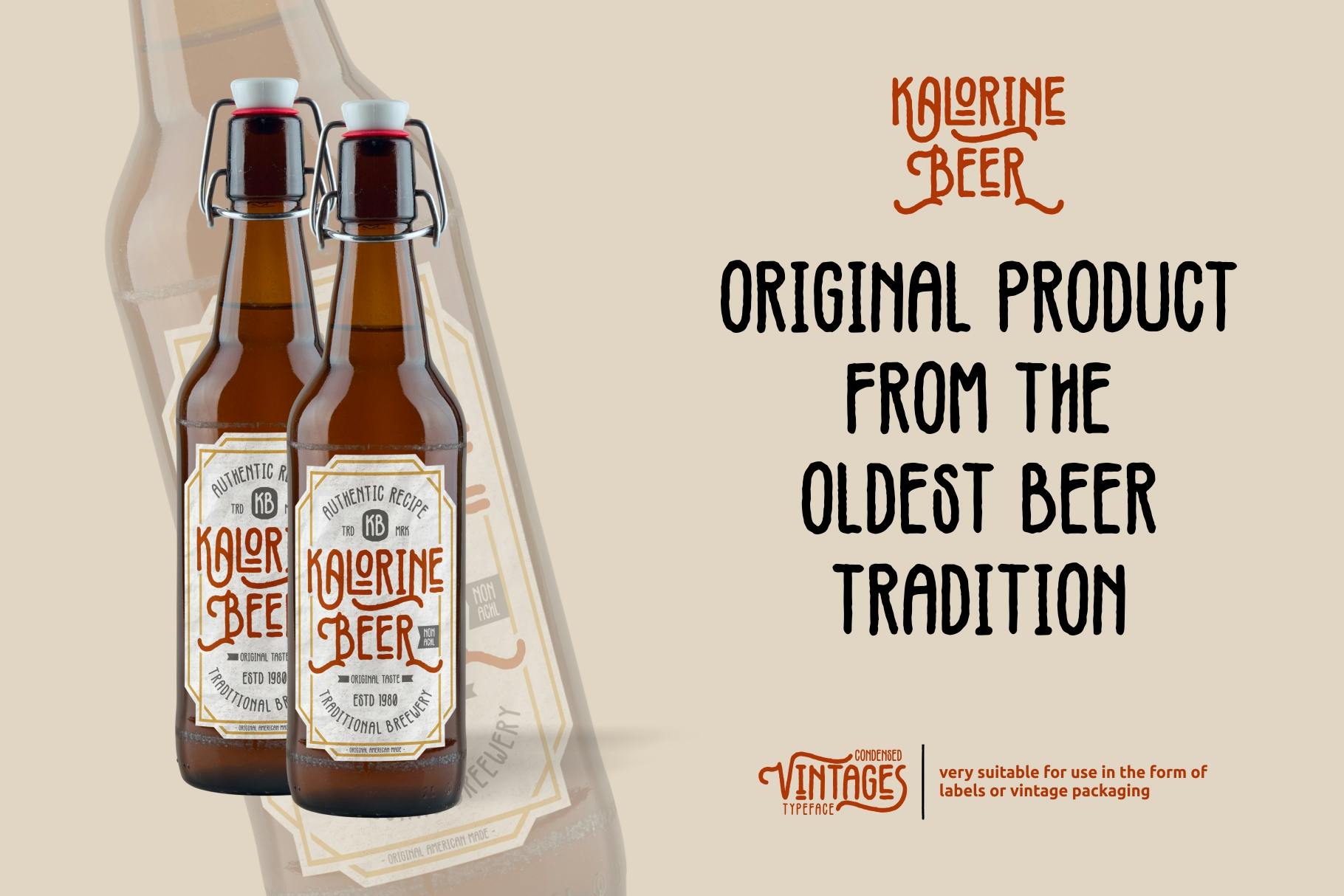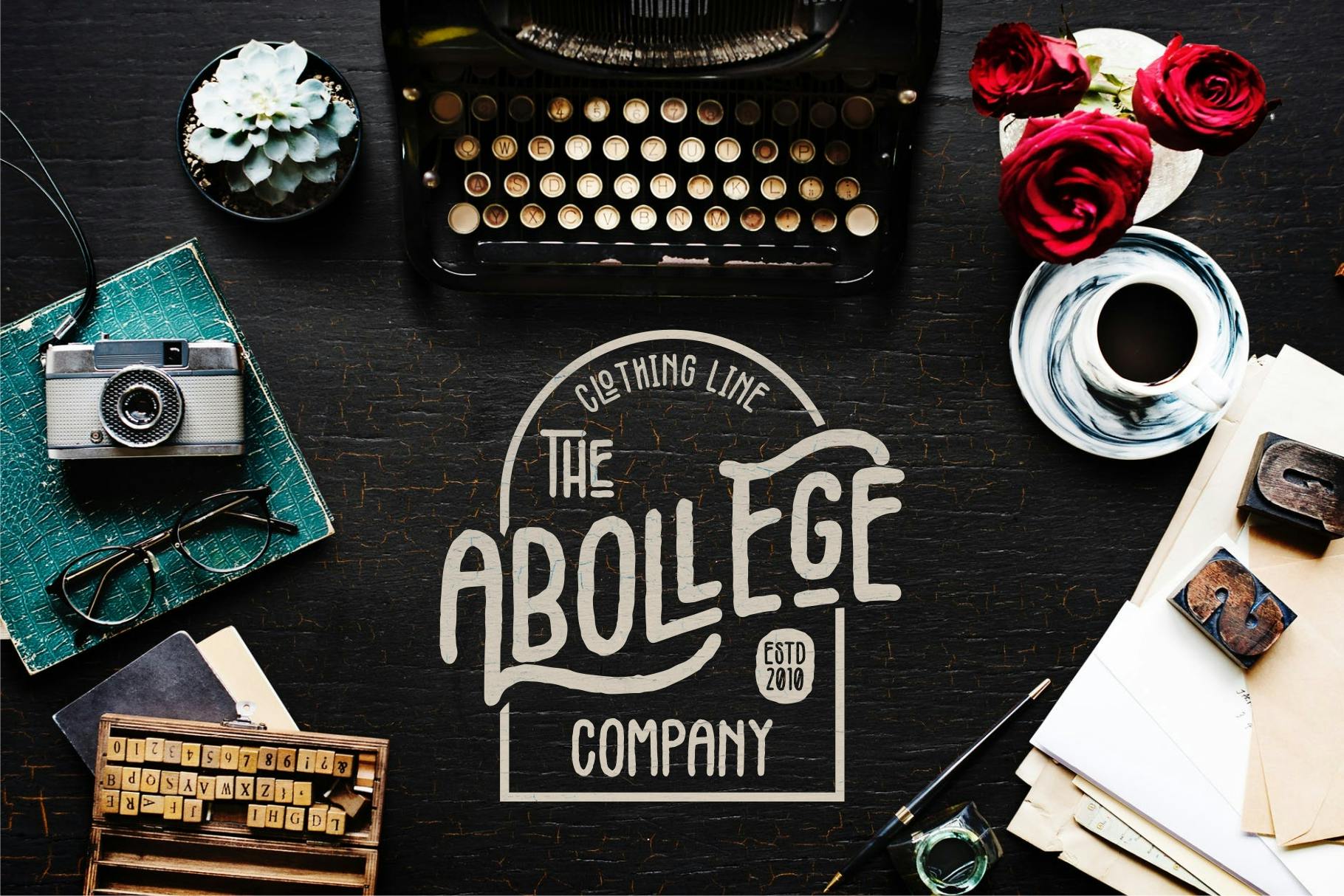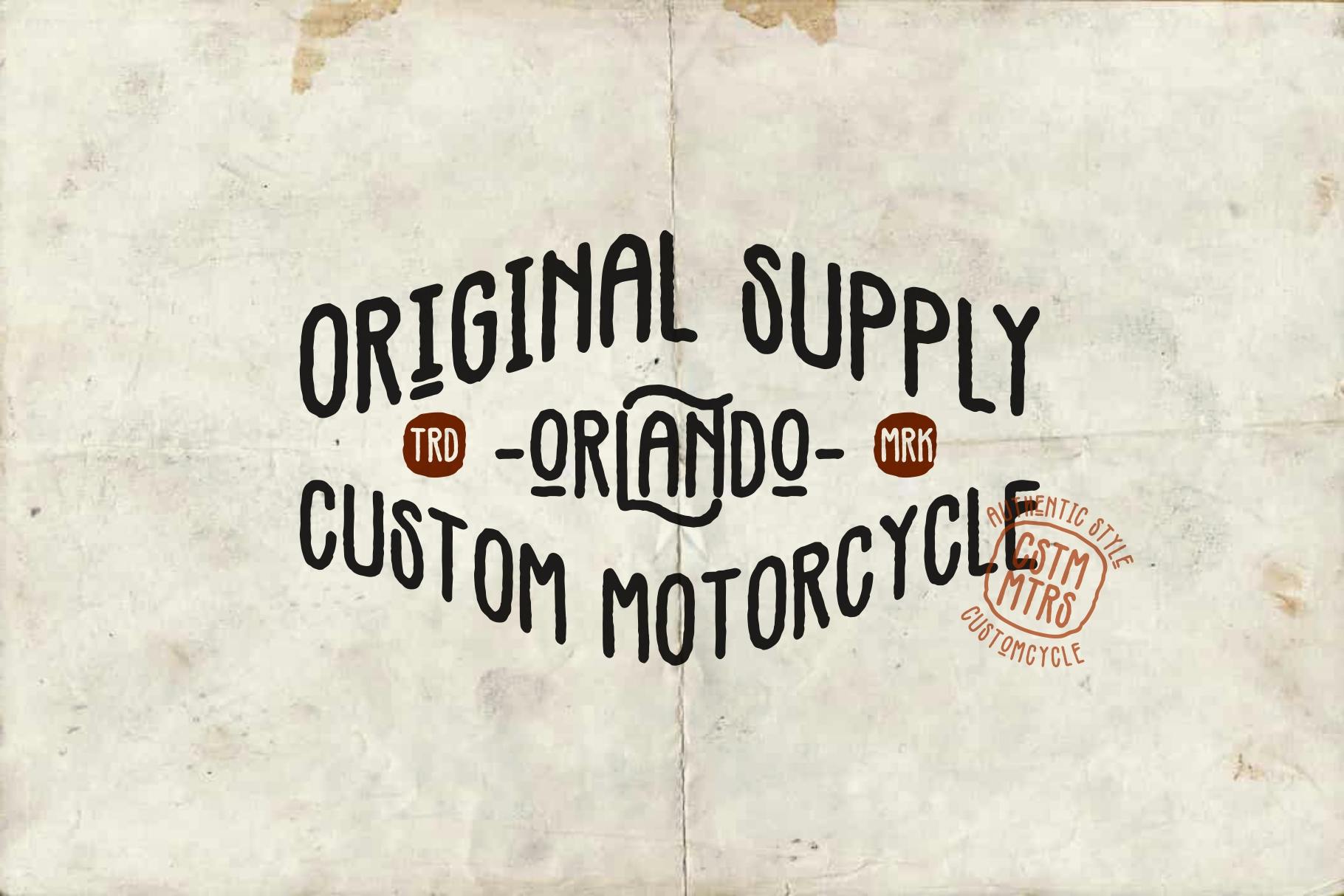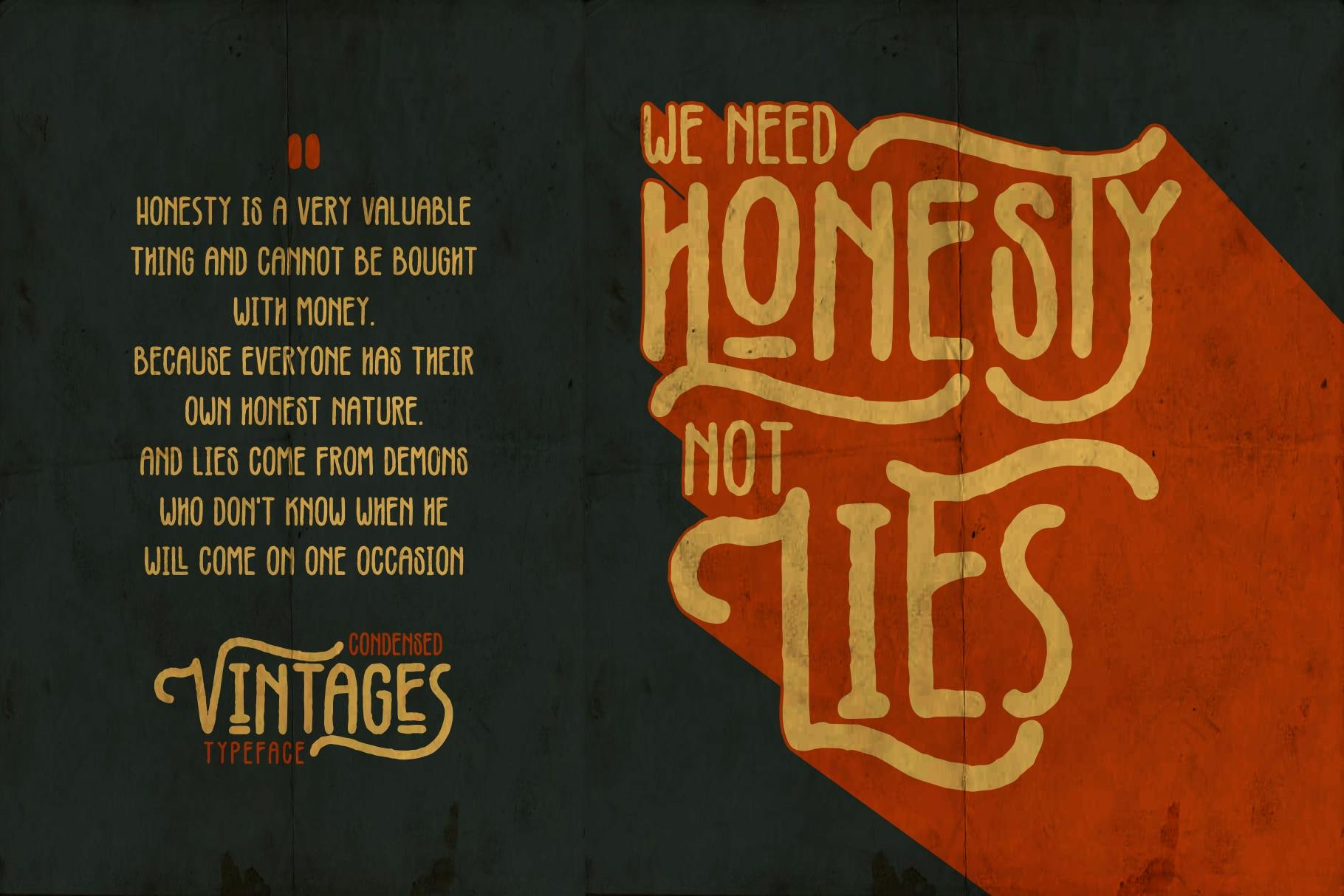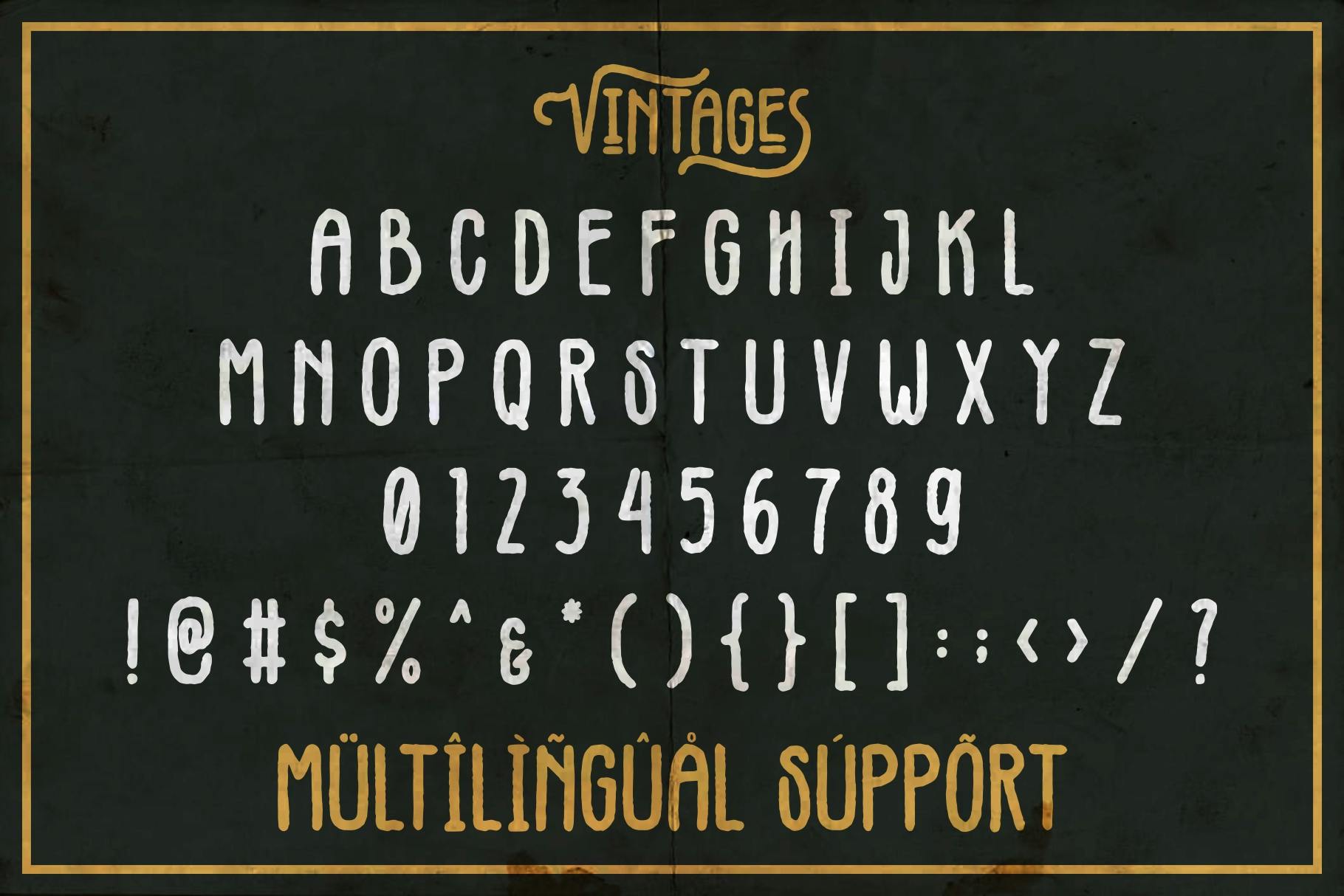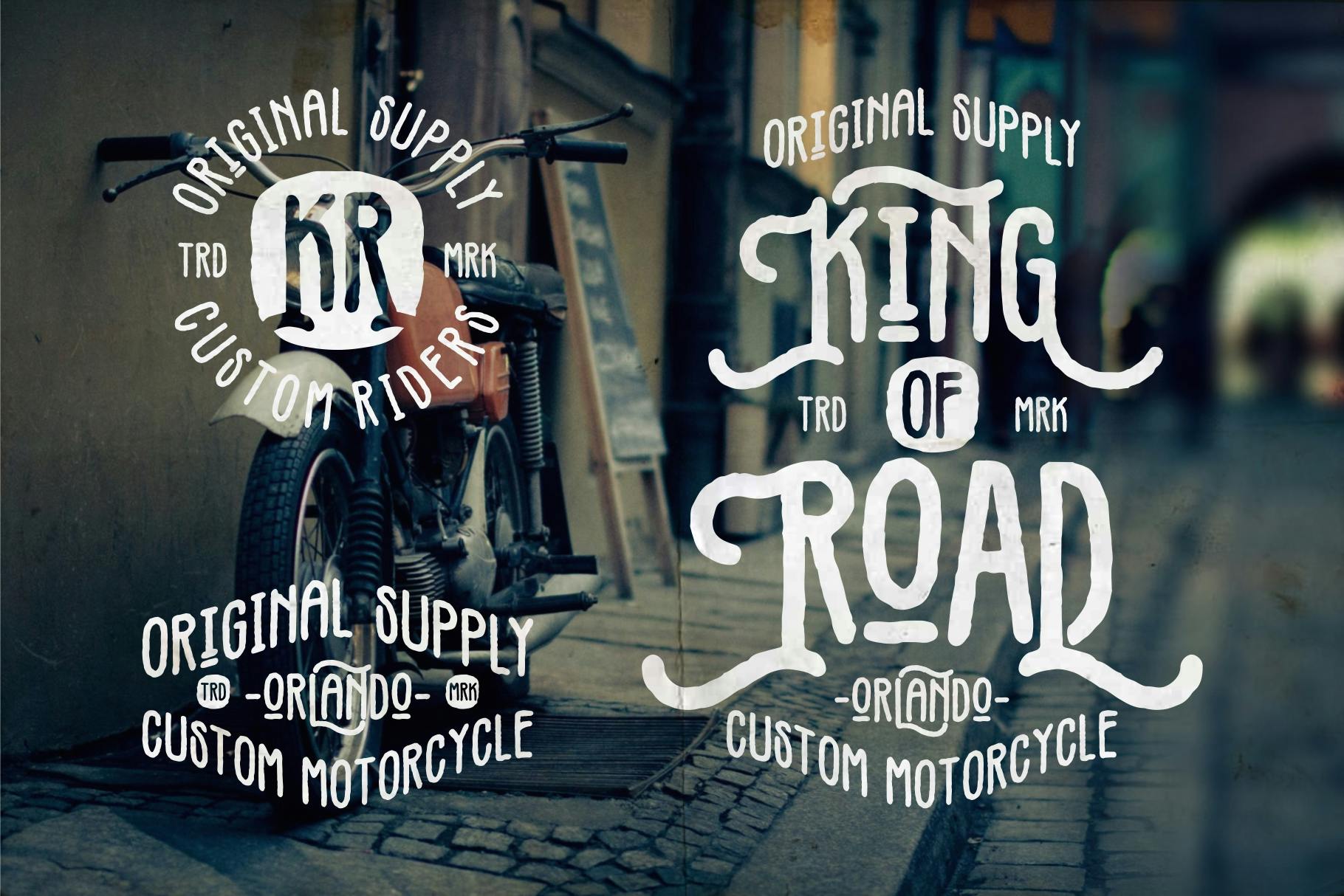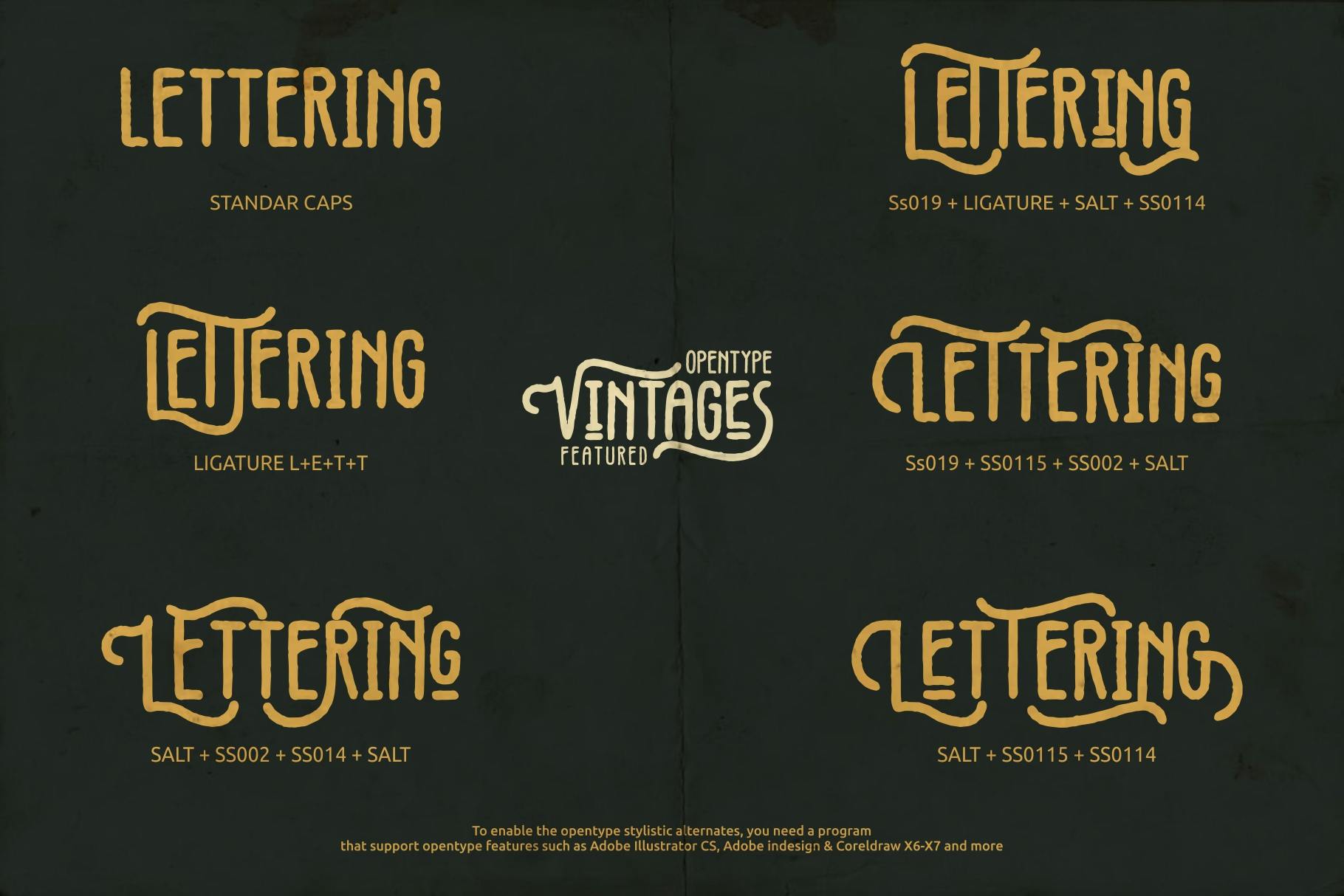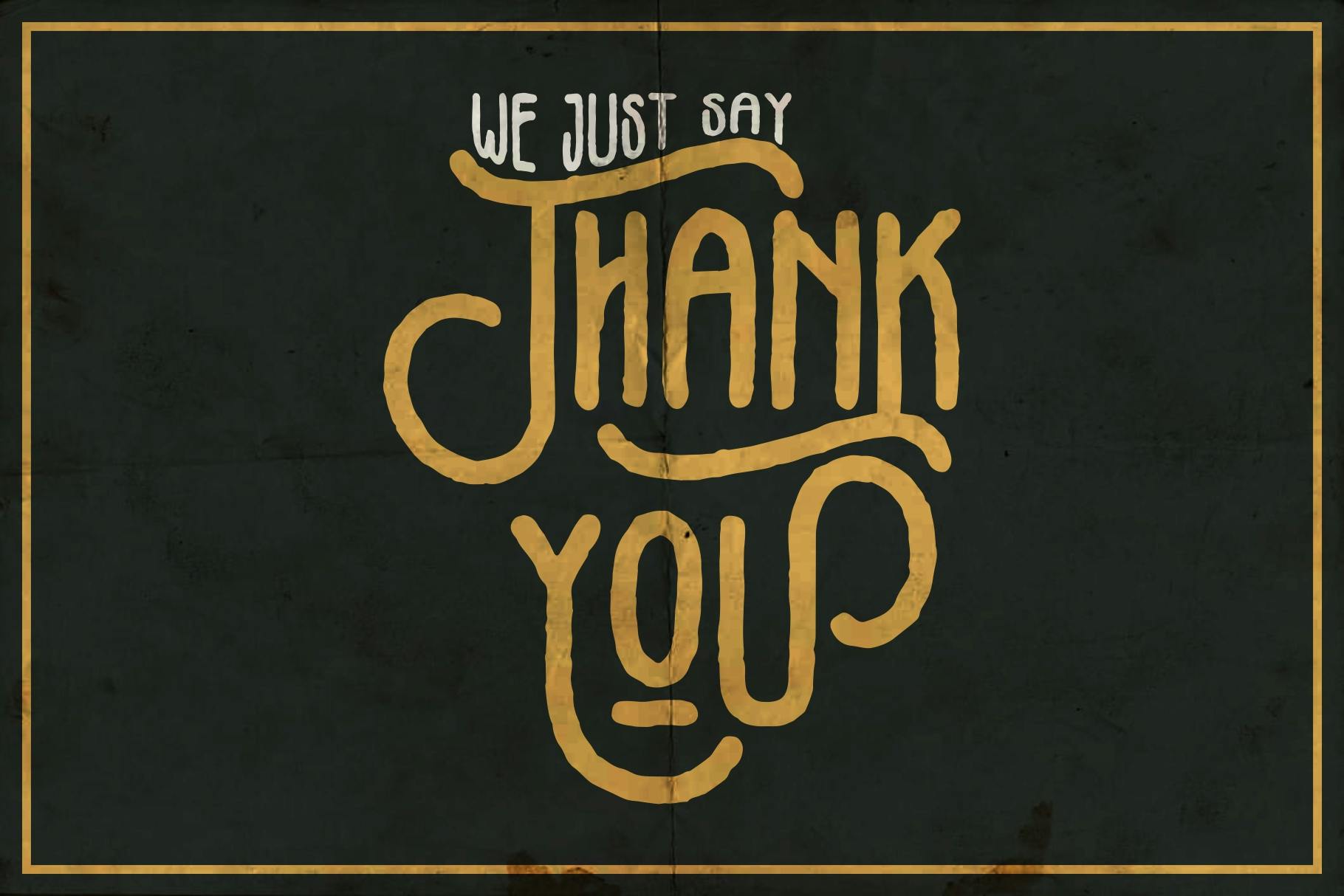
به فونت وینتیجز خوش آمدید
فونت وینتیجز یک نوع فونت مدرن و وینتیج دستساز با طراحی مونو لاین است که شامل کاراکترهای بزرگ و چیدمان فشرده میباشد. این فونت سبک کلاسیک تایپوگرافی را با طراحی مدرن دستساز ترکیب میکند.
این فونت برای پروژههای مختلفی مانند لوگو، lettering دستی، برندینگ، لیبل، طراحی تیشرت، پوستر و بسیاری دیگر مناسب است.
فونت وینتیجز دارای بیش از ۴۰۰ کاراکتر شامل ستهای استایلی، لیگاتورها و غیره است. ویژگیهای OpenType با استایلهای جایگزین و ستهای استایلی در برخی از کاراکترها به شما این امکان را میدهد که جفتهای حروف را با هم ترکیب کنید تا با طراحی شما هماهنگ شود. برای دسترسی به کاراکترهای جایگزین، به برنامهای نیاز دارید که از ویژگیهای OpenType پشتیبانی کند، مانند Adobe Illustrator CS و Adobe Indesign.